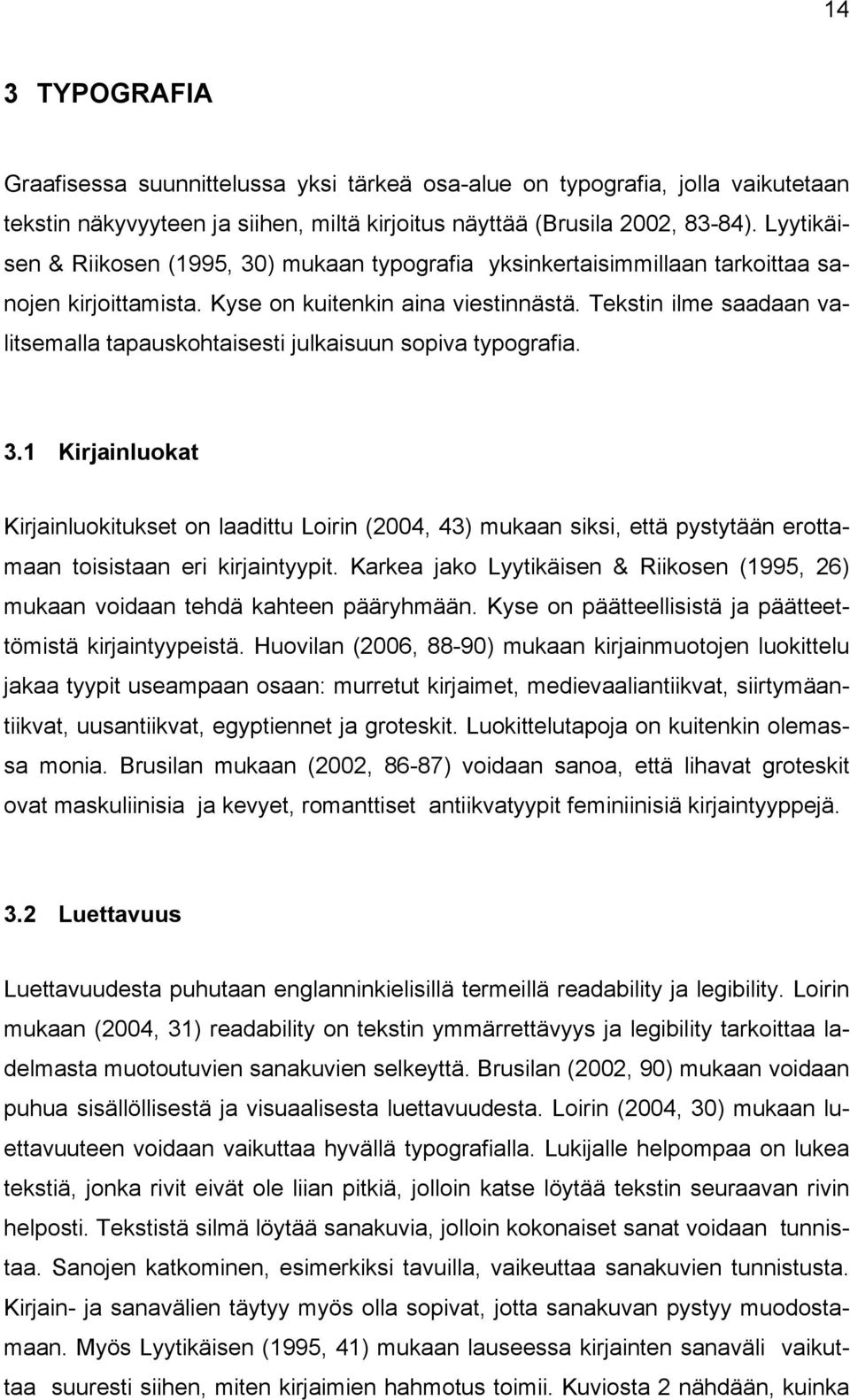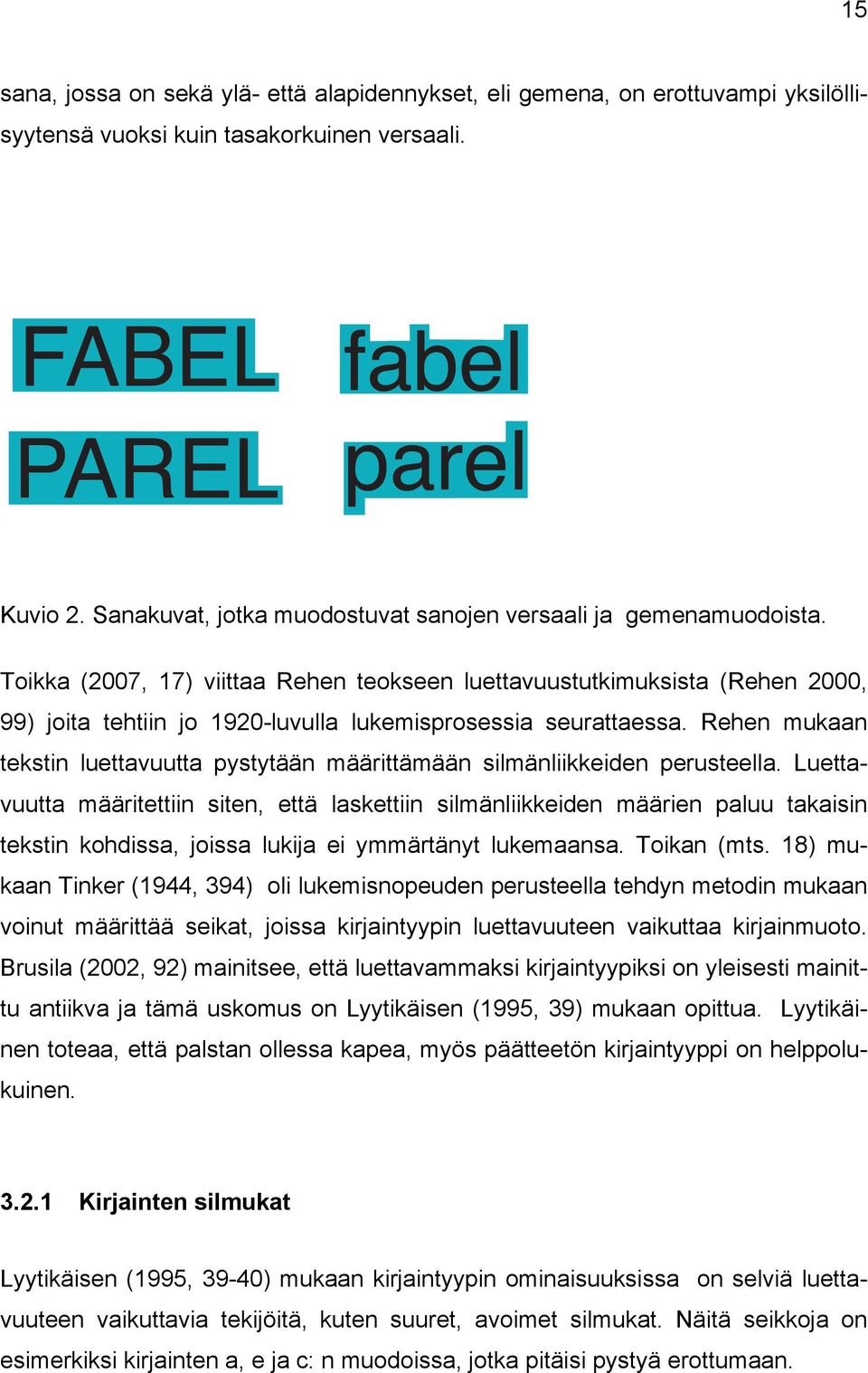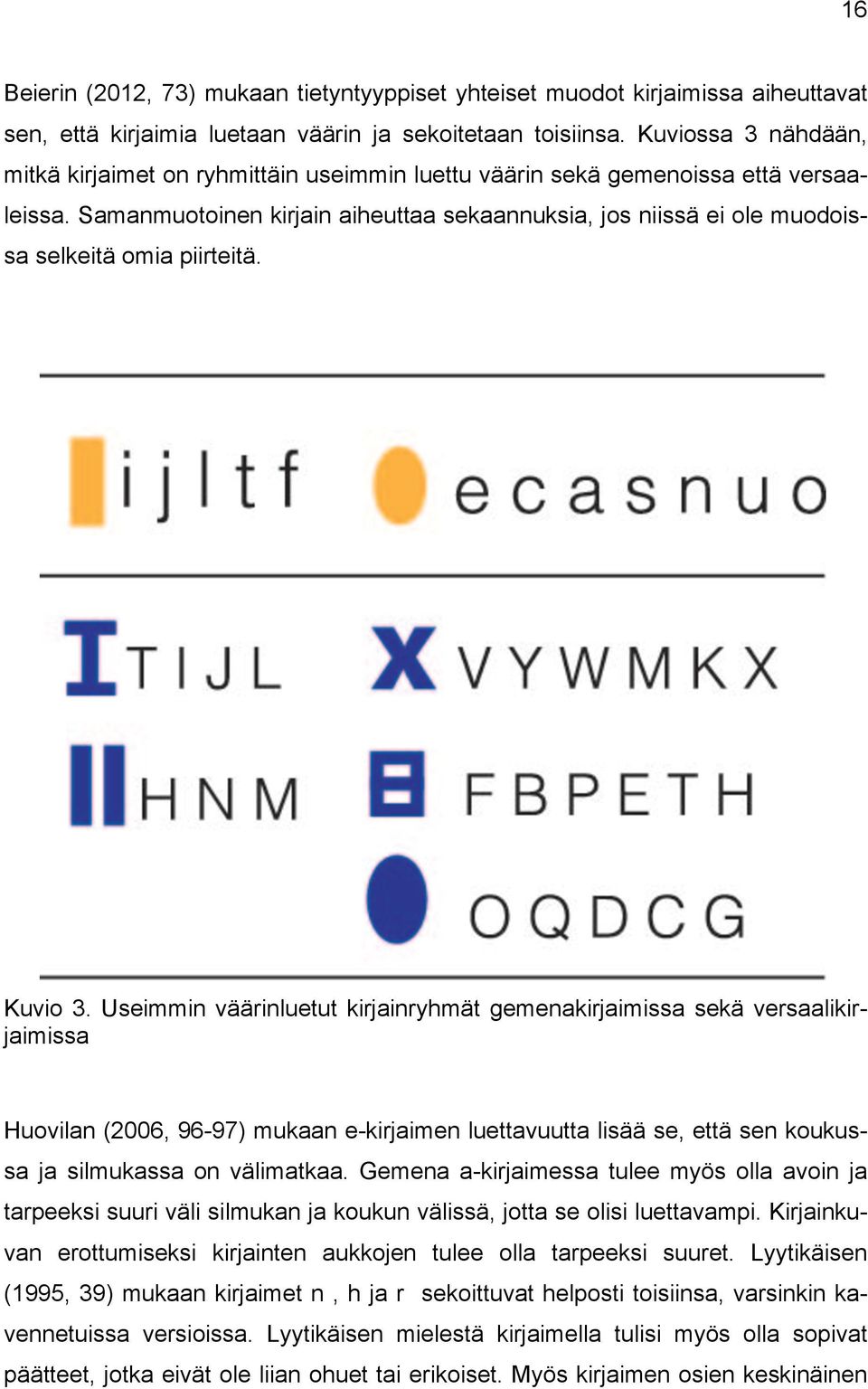
7 7 Käytetyt termit ja lyhenteet Kehitysvammaisuus Selkokieli Luettavuus Kehitysvammaisuus tarkoittaa hermoston kehityshäiriötä, johon liittyy aivojen kehityshäiriö. Kasken (2012, 16) mukaan tämän takia kehitysvammaisella on älyllisten toimintojen vajavuutta, josta käytetään nimitystä älyllinen kehitysvammaisuus. Selkokieli on Sainion (2000, 16) mukaan helppotajuista, suorasanaista kielen käyttöä. Brusilan (2002, 90) mukaan luettavuudessa voidaan puhua sisällöllisestä ja visuaalisesta luettavuudesta.
8 8 1 JOHDANTO Snäjoen ammattikorkeakoulussa järjestettiin lukuvuonna lastenkirjaprojekti, joka kuuluu vaihtoehtoisten opintojen kokonaisuuteen. Se on Snäjoen ammattikorkeakoulun muotoilun koulutusohjelman graafisen muotoilun suuntautumisalan ja kirjasto- ja tietopalvelun koulutusohjelman yhtsprojekti. Projektin tarkoituksena on tänä vuonna suunnitella lasten erityisryhmille tarkoitettuja tai maailmankatsomuksellisia aihta käsitteleviä kuvakirjoja. Tarkoituksena on, että opiskelijat suunnittelevat kirjat joko yksin tai ryhmissä prototyypksi asti. Kirjojen protoista järjestetään Lastenkirjanäyttely toukokuussa 2013 Snäjoen Kaupunginkirjaston tiloissa. Edellinen Layers -lastenkirjaprojekti aloitettiin syksyn 2011 aikana ja se huipentui Layers -lastenkirjat -näyttelyyn Vaasan kaupunginkirjastoon keväällä Tavoitteena oli silloin suunnitella satutuntikäyttöön soveltuvia koklevia kirjoja. Kirjat olivat todella suosittuja, minkä ansiosta Layers-lastenkirjanäyttely kiersi Vaasan lisäksi myös parissa muussakin kirjastossa. Layers-lastenkirjat olivat esillä myös Snäjoella järjestetyssä Kirjakori 2011 tapahtumassa Kirjakoritapahtuma on lastenkirjainstituutin järjestämä tapahtuma, jossa esitellään edellisen vuoden lastenkirjasatoa. Tässä opinnäytetyössäni suunnittelen kuvakirjan lukemaan opetteleville kehitysvammaisille lapsille ja keskityn kuvakirjan typografiaan ja siinä lähinnä kirjainmuotojen tarkasteluun. Kohderyhmän haasteellisuus kiehtoi, oli otettava huomioon erityisryhmän tarpeet. Kehitysvammaiset on valittu tutkimushenkilöiksi siksi, että hllä on normaalia suurempia vaikeuksia kirjainten hahmottamisessa sekä muita rajoittta. Teemme kirjan yhtstyössä Suvi Tamsin kanssa, jonka tehtävänä oli suunnitella kirjaan kuvitukset. Kuvakirjan teksti on lastenkirjailija Mervi Hkkilän satu Siivet. Syksyllä 2012 selvittelin aiheen taustoja syventävissä opinnoissamme ja koska tulokset olivat hieman ristiriitaisia, jatkan kuvakirjan typografian tiimoilta opinnäytetyössäni. Keskityn työssäni käsittelemään enemmän groteskeja, koska niitä on tutkittu vähemmän kuin antiikvoita. Lastenkirjaprojektin vaihtoehtoisissa opinnois-
9 9 sa valmistan kirjan lopulliseen muotoonsa tässä opinnäytetyössä saatujen tulosten perusteella. Aiheena kehitysvammaisille lapsille suunnattu kuvakirja on ajankohtainen, koska syventävien opintojen yhteydessä haastatellessamme kehitysvammaisten ja erityislasten opettajia selvisi, että erityisopetusta tarvitsevien lasten määrä on kasvamassa. Opettajat kertoivat, että oppimateriaalien määrä ole kuitenkaan kasvanut. Lisäksi haastatteluissa opettajat kertoivat tekevänsä itse paljon oppimateriaalia, lähinnä lkkaa ja liimaa -menetelmällä. Syksyllä 2012 syventävien opintojeni aiheena oli tutkia auttaako kuvaan integroitu teksti kehitysvammaisia lapsia lukemaan oppimisessa. Tekstin integrointi tarkoittaa tiukasti kuvaan liitettyä tekstiä. Syventävien opintojeni työssä sain paljon tietoa kehitysvammaisista lapsista, kun haastattelin kahta kehitysvammaisten lasten luokanopettajaa. Hllä oli paljon näkemyksiä siitä, millaisia skkoja tulisi ottaa huomioon kirjaa suunnitellessa, koska käyttäjien taso ja huomiokyky on rajallinen. Opettajat puhuivat haastattelussa versaalikirjainten eli suuraakkosten puolesta. He pitivät niitä paremmin tunnistettavina ja ne siten soveltuisivat paremmin lukemaan opettelussa kehitysvammaisille lapsille. Toinen opettajista oli sitä mieltä, että myös gemenakirjaimia eli pienaakkosia tulisi opetella suuraakkosten ohella. He olivat yhtä mieltä siitä, että kuvakirjan kirjaintyyppi pitäisi olla päätteetöntä. Testitilantssa nämä skat selvenivät, sillä päätteellinen kirjaintyyppi oli melko hankala lukea. Molemmat opettajat toivoivat, että kirjan teksti olisi tavutettua. Lukemaan oppimisessa kehitysvammaiset lapset ovat haasteellisempia kuin tavalliset koululaiset. Siksi olisi kiinnostavaa saada tietää millaisin graafisin knoin saadaan kehitysvammaisten lasten huomio kirjan tekstiin ja millainen typografia olisi hlle soveltuvaa. Tutkimuskysymykseksi muotoutuu millaiset ominaisuudet kirjaimessa tulisi olla, että kehitysvammainen lapsi pystyisi helposti lukemaan tekstiä? Tutkimusmenetelmänä tässä opinnäytetyössä on osallistuva havainnointi ja testaaminen. Osallistuvassa havainnoinnissa testataan tässä testitilanteessa kehi-
10 10 tysvammaisten lasten huomiokykyä tekstin asettelun suhteen ja millainen teksti on sellaista, mitä he pystyvät lukemaan. Testikuvissa on osia kuvakirjan kohtauksista. Testikuvissa on erilaisia virikktä ja pyrkimys on saada lapset huomaamaan ne. Virikkssä olevalla typografialla testataan, millainen typografia erottuu. Koska kehitysvammaiset lukemaan opettelevat lapset käyvät koulua erityisluokilla normaalissa kouluympäristössä, suoritamme testauksia koulussa erityisluokkien parissa. Koehenkilöinä tutkimuksessa olivat kohderyhmän kaltaiset oppilasryhmät eli kehitysvammaiset lukemaan opettelevat lapset. Testauksessa oli erityisryhmän lapsia neljän eri koulun luokalta. He ovat osittain samoja oppilaita kuin syventävissä opinnoissa testauksissa mukana olleet. Opinnäytetyöni aihe kuuluu graafisen suunnittelun alalla julkaisugrafiikkaan ja typografiaan. Työn yritysyhtstyökumppanina on Kustannusosakeyhtiö Tammi, joka on markkinajohtaja lasten- ja nuortenkirjoissa. Tarkoituksena on valmistaa kuvakirjan prototyyppi ja saada kustantaja kiinnostumaan kirjasta.
11 11 2 KEHITYSVAMMAISET JA LUKEMAAN OPETTELEMINEN 2.1 Kehitysvammaisuus tarkoittaa hermoston kehityshäiriötä, johon liittyy aivojen kehityshäiriö. Kasken (2012, 16) mukaan tämän takia kehitysvammaisella on älyllisten toimintojen vajavuutta, josta käytetään nimitystä älyllinen kehitysvammaisuus. Älylliseen kehitysvammaisuuteen voivat liittyä myös muut kehityshäiriöt, lisävammat ja sairaudet, kuten aisti-, puhe- ja liikuntavammat, epilepsia, autismi, mielenterveyden häiriöt ja haastava käyttäytyminen (Kaski 2012, 18). Uusien asioiden oppimisen vaikeus on Kasken (2012, ) mukaan älyllisesti kehitysvammaisilla tavallista, joka johtuu ymmärtämisen alueella olevasta vammasta. Hllä on vaikeuksia hyödyntää jo opittuja asioita, jos tilanne on uusi tai muuttunut. Ihmiset, jotka ovat lievästi kehitysvammaisia, voivat ajattelun varassa oppia jäsentämään todellisuutta. Yksinkertaisten symbolien ymmärtäminen sekä lukemaan ja kirjoittamaan oppiminen on hlle täysin mahdollista. 2.2 Kehitysvammaisten lukemaan opettelu Kehitysvammaisilla lapsilla on myös oppivelvollisuus ja he saavat oman tasonsa mukaista opetusta. Koulussa kehitysvammaiset lapset ovat erityisluokissa, kuten harjaantumisluokissa ja pienluokissa. Nykyisin saatetaan puhua myös vain erityistä tukea tarvitsevista oppilaista, koska erityisluokan oppilailla on niin monenlaisia kehityshäiriöitä ja sairauksia. Erityisopettajien haastatteluissa, joita tehtiin syventävissä opinnoissa, tuli ilmi, että kehitysvammaisten lasten lukemaan opettelu saattaa kestää usta vuosia, koska hllä on huono muisti. Tästä syystä kehitysvammaiset lapset tarvitsevat paljon toistoa ja oppilaat etenevät luokissa kukin omaan tahtiinsa. Koska kehitysvammainen lapsi on haastavampi oppija kuin tavallinen lapsi, on hyvä ottaa huomioon skkoja, jotka voivat olla avuksi lukemaan opettelussa. Kehitysvammaisille suun-